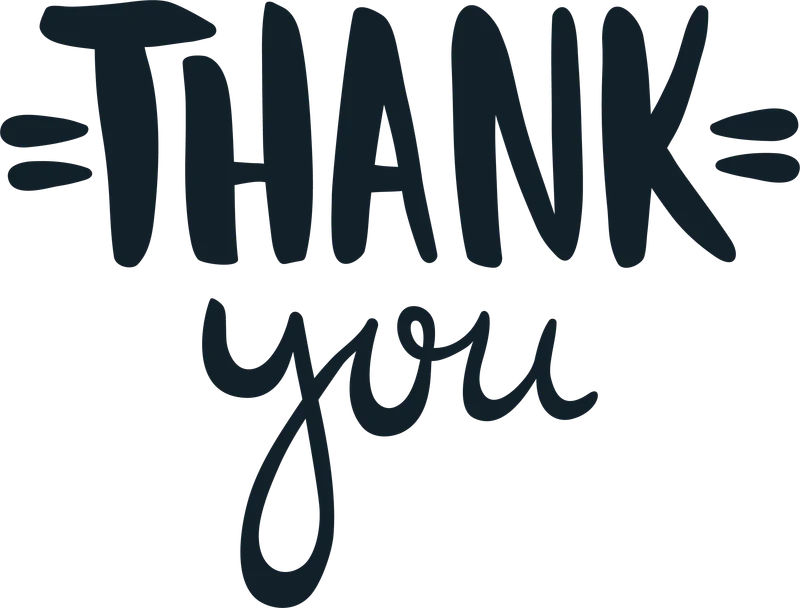
Lời cảm ơn ý nghĩa, font chữ viết tay độc đáo
Lời cảm ơn ý nghĩa, font chữ viết tay độc đáo — Mẫu thiết kế chữ 'Thank you' viết tay độc đáo, mang thông điệp cảm ơn chân thành. Phù hợp in áo, túi, quà tặng.
Trong hình có: chữ viết, lời cảm ơn
Phong cách: line-art · Cảm giác: biết ơn